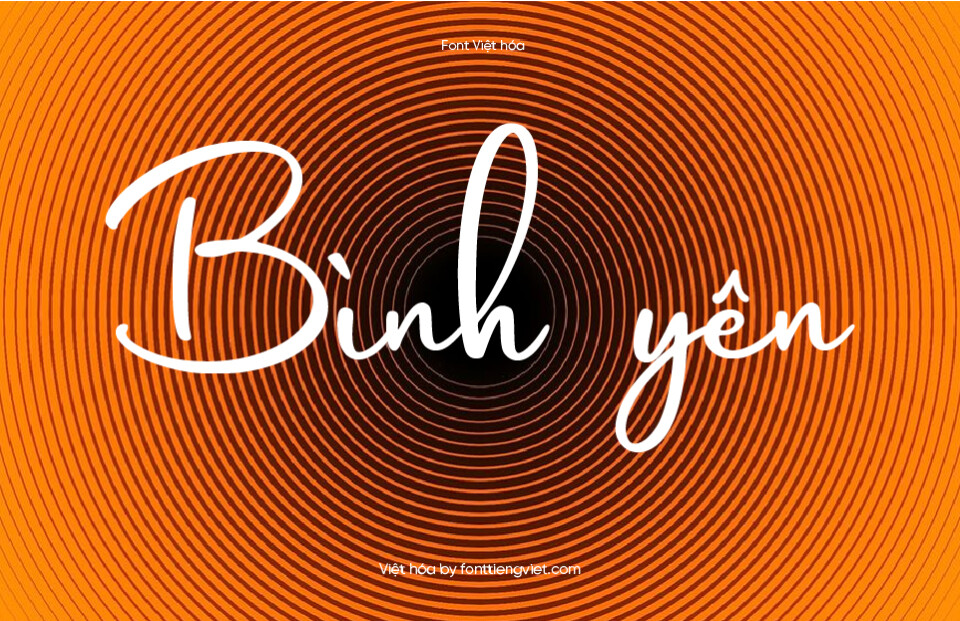
Sự lựa chọn Font Chữ đóng vai trò cực kỳ quan trọng trong việc tạo nên ấn tượng thị giác mạnh mẽ cho bất kỳ dự án thiết kế nào. Trong thế giới typography đa dạng, “Font Việt hóa 1FTV VIP Bostanic Millague” nổi lên như một lựa chọn hoàn hảo, mang đến sự kết hợp độc đáo giữa vẻ đẹp cổ điển và nét hiện đại, đặc biệt là khả năng hỗ trợ tiếng Việt đầy đủ và tinh tế. Đối với các nhà thiết kế đồ họa, sinh viên mỹ thuật hay bất kỳ ai đang tìm kiếm một bộ font chất lượng cao để thể hiện ý tưởng của mình, Bostanic Millague Việt hóa hứa hẹn sẽ là một công cụ đắc lực, mở ra không gian sáng tạo không giới hạn.
Font Việt hóa 1FTV VIP Bostanic Millague: Sự Kết Hợp Hoàn Hảo
Bostanic Millague không chỉ là một font chữ thông thường; nó là một tác phẩm nghệ thuật typography được “Việt hóa” một cách tỉ mỉ bởi 1FTV VIP, mang đến trải nghiệm tuyệt vời cho người dùng Việt Nam. Với các đường nét mềm mại, uyển chuyển nhưng vẫn giữ được sự mạnh mẽ và sang trọng, Bostanic Millague tạo nên một phong cách riêng biệt, khó lẫn vào đâu được. Sự tỉ mỉ trong từng ký tự, từ dấu câu đến các dấu thanh của tiếng Việt, đều được chăm chút kỹ lưỡng, đảm bảo tính thẩm mỹ cao nhất và khả năng đọc tốt trong mọi ngữ cảnh. Đây chính là yếu tố then chốt giúp font này trở thành lựa chọn hàng đầu cho những dự án yêu cầu sự tinh tế và chuyên nghiệp.
Tại Sao Bạn Nên Chọn Bostanic Millague Việt Hóa?
Có vô số lý do để “Font Việt hóa 1FTV VIP Bostanic Millague” trở thành một cái tên được săn đón trong cộng đồng thiết kế. Đầu tiên và quan trọng nhất, đó là khả năng tương thích hoàn hảo với tiếng Việt. Việc Việt hóa không chỉ đơn thuần là thêm dấu mà còn là quá trình điều chỉnh khoảng cách, độ cao và độ dày của từng ký tự để chúng hòa hợp một cách tự nhiên nhất. Điều này giúp các văn bản tiếng Việt trông chuyên nghiệp, mạch lạc và dễ đọc hơn rất nhiều, tránh được các lỗi hiển thị phổ biến ở các font không được Việt hóa kỹ lưỡng. Hơn nữa, phong cách thiết kế của Bostanic Millague mang đến một vẻ đẹp thanh lịch, rất phù hợp cho các ấn phẩm cao cấp, thiệp mời, logo thương hiệu hoặc tiêu đề website.
Thứ hai, tính linh hoạt của font này là một điểm cộng lớn. Dù bạn đang thiết kế một tờ rơi quảng cáo mang phong cách vintage, một bìa sách hiện đại hay một bài thuyết trình học thuật, Bostanic Millague đều có thể thích ứng một cách ấn tượng. Sự cân bằng giữa nét cổ điển và hiện đại giúp nó dễ dàng phối hợp với nhiều yếu tố thiết kế khác, từ hình ảnh đến màu sắc, tạo nên tổng thể hài hòa và thu hút. Sự đa dạng trong các biến thể của font (nếu có) cũng mở rộng khả năng sáng tạo, cho phép người dùng tùy chỉnh để phù hợp nhất với thông điệp muốn truyền tải.
Ứng Dụng Thực Tiễn của Font Bostanic Millague trong Đời Sống và Học Tập
Đối với học sinh, sinh viên, đặc biệt là những người theo học các ngành liên quan đến nghệ thuật, thiết kế đồ họa hoặc truyền thông, việc sở hữu và biết cách sử dụng một bộ font chất lượng như Bostanic Millague là một lợi thế không nhỏ. Trong các bài tiểu luận, báo cáo hoặc đồ án tốt nghiệp, một font chữ đẹp và chuyên nghiệp có thể giúp nâng cao giá trị thẩm mỹ, tạo ấn tượng tốt hơn với giáo viên và ban giám khảo. Nó không chỉ đơn thuần là truyền tải thông tin mà còn là cách thể hiện sự đầu tư, tỉ mỉ của người thực hiện.
Trong lĩnh vực thiết kế thương mại, “Font Việt hóa 1FTV VIP Bostanic Millague” là một lựa chọn tuyệt vời cho việc xây dựng nhận diện thương hiệu. Từ logo, danh thiếp, bao bì sản phẩm cho đến các chiến dịch quảng cáo trên mạng xã hội, font này đều có thể góp phần tạo nên một hình ảnh thương hiệu độc đáo, sang trọng và dễ nhận biết. Các doanh nghiệp muốn tạo sự khác biệt và thu hút khách hàng mục tiêu sẽ tìm thấy giá trị to lớn từ việc tích hợp Bostanic Millague vào bộ công cụ thiết kế của mình.
Đối với các nhà phát triển nội dung, việc sử dụng các từ khóa liên quan như “font chữ đẹp cho thiết kế”, “phông chữ Việt hóa”, “typography chuyên nghiệp” cùng với từ khóa chính “Font Việt hóa 1FTV VIP Bostanic Millague” sẽ giúp bài viết của bạn dễ dàng tiếp cận hơn với những người đang tìm kiếm các giải pháp font chữ chất lượng cao. Đừng quên đặt từ khóa vào các thẻ
và
một cách tự nhiên để Google hiểu rõ hơn về chủ đề nội dung.
Việc đầu tư vào một bộ font chất lượng như Bostanic Millague không chỉ là đầu tư vào công cụ mà còn là đầu tư vào giá trị thẩm mỹ và sự chuyên nghiệp của bản thân hoặc thương hiệu. Nó giúp các nhà thiết kế tạo ra những sản phẩm độc đáo, ấn tượng, trong khi các học sinh, sinh viên có thể trình bày ý tưởng của mình một cách tinh tế và hiệu quả hơn. Hơn nữa, việc sử dụng font Việt hóa chất lượng còn thể hiện sự tôn trọng đối với ngôn ngữ mẹ đẻ và nâng cao trải nghiệm người dùng Việt Nam.
Tóm lại, “Font Việt hóa 1FTV VIP Bostanic Millague” không chỉ là một phông chữ; nó là một cầu nối giữa nghệ thuật truyền thống và công nghệ hiện đại, mang đến sự hoàn hảo cho mọi dự án. Dù bạn là một chuyên gia thiết kế, một sinh viên đang chuẩn bị cho kỳ thi tốt nghiệp, hay một người đam mê sáng tạo, việc khám phá và sử dụng font này chắc chắn sẽ mở ra những tiềm năng mới, giúp bạn tạo ra những tác phẩm thực sự nổi bật. Hy vọng qua bài viết này, bạn đã có cái nhìn sâu sắc hơn về giá trị mà Font Chữ đặc biệt này mang lại và sẵn sàng áp dụng nó vào các dự án của riêng mình.